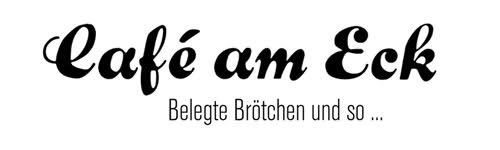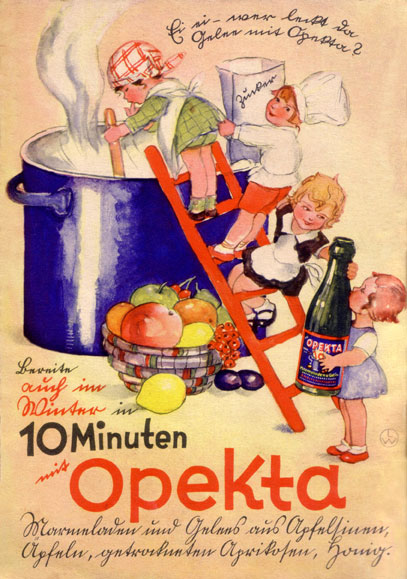
Welche Schrift ist das
Für bereits im Forum erwähnte Filmproduktion bin ich gerade daran eine Rechnung eines alten Berliner Cafe zu "basteln".
Auf dem Bild interessiert mich also vor allem der Schriftzug Hotel Adlon.
Aber auch die serifenlose Schrift in der Rechnung selber, wäre interessant zu kennen.
bzw. gibt es ein Satzschrift von vor 1937, die die Anmutung einer Handschrift hat (hatte).
Ich habe eine Monotype Corsiva auf dem Rechner, die zwar ursprünglich bereits aus dem 16Jhd stammt, bin mir aber äußerst unsicher ob diese als Satzschrift in den 30er Jahren in Europa genutzt wurde. Eher nicht, oder?
Ach ja, eine Edwardian Script, French Script und Gabriola besitze ich auch noch. Zu denen ich allerdings keine genauen Informationen über Herkunft und Erstellungsdatum finde, geschweige denn ob diese evtl im Berlin der 30er genutzt wurden.
Beim Briefkopf würd ich auf handgeschnitzt tippen; so wie die Buchstaben gerade bei »Hotel Adlon« gegenseitig einander ins Fleisch ragen, ich bezweifle, dass das mit Bleilettern machbar war ... :?
Danke. Die Bernhard Schoenschrift könnte ich wohl nehmen, wenn ich nicht selber zeichnen möchte. Mal sehen was der Zeitdruck am Ende daraus macht :-)
Die Brush Script find ich dann doch etwas wuchtig.
Naja, es ging ja um irgendein Café, nicht ums Adlon – da muss so eine Werbeschrift nicht verfehlt sein, kann ja auch was für die unteren Klassen gemeint sein :?
Och ... Vielleicht wären ja meine Ansprüche im Berlin der Dreißigerjahre nicht so hoch gewesen ...? ;)
Könnt man schon mal machen, schließlich waren ja auch damals nicht nur Meistergestalter unterwegs ;)
Ich vermute, wir haben uns mißverstanden. Du meintest wahrscheinlich irgendeine Brush, ich meinte die Brush:
Die wäre ohnehin verfehlt.
Schätz ich auch – ich hab oben zur Bernhard-Brushscript verlinkt, ich nehm an der OP bezog sich darauf :D
Ja, das hatte ich übersehen. Wenn ich Brush Script lese, setzt ein automatischer Abwehrmechanismus ein, der sich natürlich nicht auf die Bernhard bezieht.
Wenn ich Brush Script lese, setzt ein automatischer Abwehrmechanismus ein [...]
[EDIT] Vergessen: Die ist echt super! Genial![ENDE]
Anderer hammerloser Schlag vor den Kopf, AKA Vorschlag:
Die FF Bau ist doch eine Digitalisierung der Schelterschen Grotesk. Wie authentisch sie ist, weiß ich allerdings nicht. :?
Die Corsiva gab’s damals übrigens nicht, genausowenig die Gabriola. Eine Schrift ähnlich der French Script (von Monotype) könnte es gegeben haben, in Deutschland war sowas jedenfalls nicht üblich. Die Edwardian Script würde noch am besten passen, ähnliche Schriften gab’s damals, wenn sie auch manche meiner Meinung nach ungewöhnliche Buchstabenformen hat.
Die FF Bau paßt ein bißchen besser als die AG:
Die ist schön :D
By the way, es hat bisher noch niemand im Zusammenhang mit diesem Filmprojekt die Gebrochenen angesprochen ... Ist jetzt nicht mein Fachgebiet – wie verbreitet waren die denn damals in Deutschland in ... tja, Firmenidentitäten? Die wurden als »Deutsche Schrift« doch sicher nicht nur im Mengensatz und auf Plakaten verwendet, oder? :? Oder war das in den Mittdreißigern schon wieder total aus der Mode ...?
Ist das nicht eher eine Deutsche Kurrentschrift? :?
Die Sütterlin ist ja eigentlich aufrecht und linear.
Da hast du recht. Eigentlich ist Sütterlin ein Form der deutschen Kurrentschrift, so ist es eigentlich richtig. Aber da Sütterlin die bekannteste Kurrentschrift ist, wird die Benennung oft auf alle deutschen Kurrentschriften übertragen.